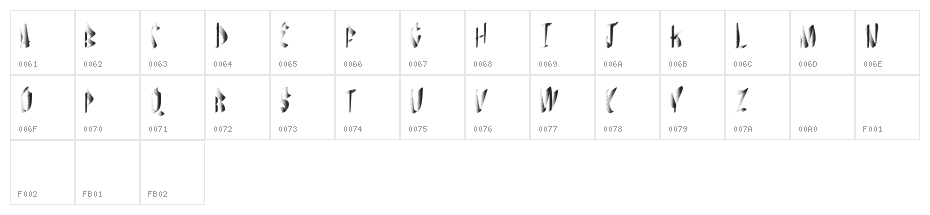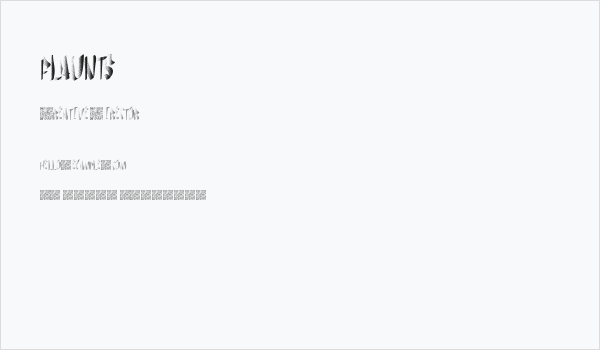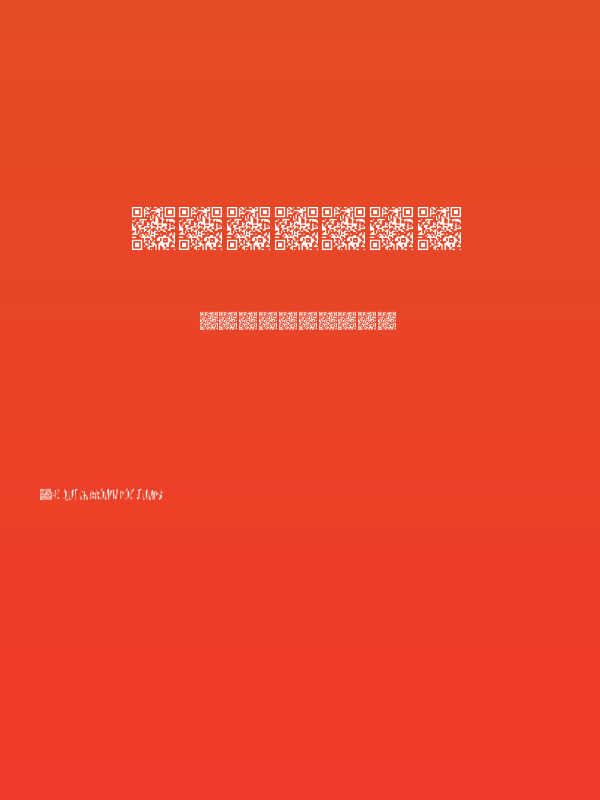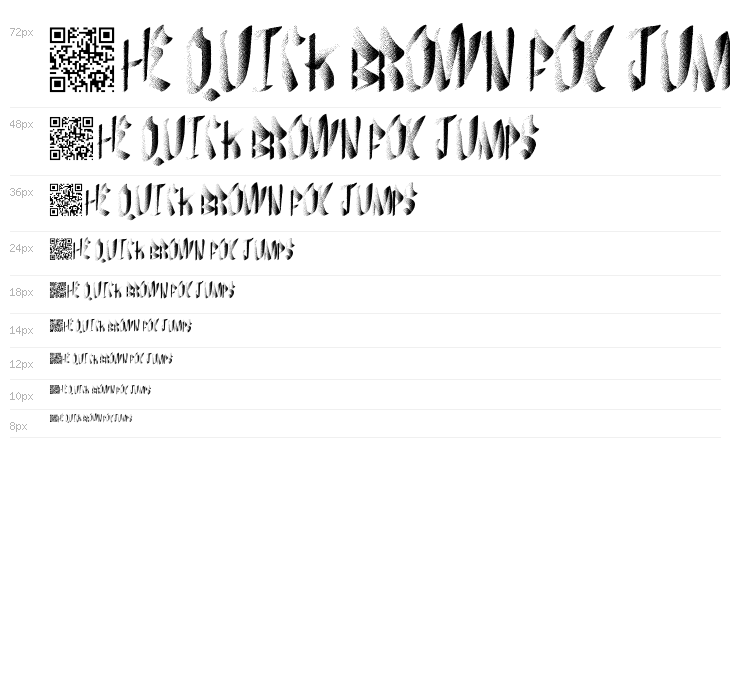
flaunts Font
✎ Thick
FLAUNTS 大写
FLAUNTS 小写
FLAUNTS 其它煤焦
| 分类 | Thick |
| 整体风格 | Modern, Artistic |
| 使用场景 | Headlines, Logos, Artistic Projects |
| 推荐项目 | Ideal for artistic posters, album covers, branding for creative industries, and any project requiring a bold, artistic statement. |